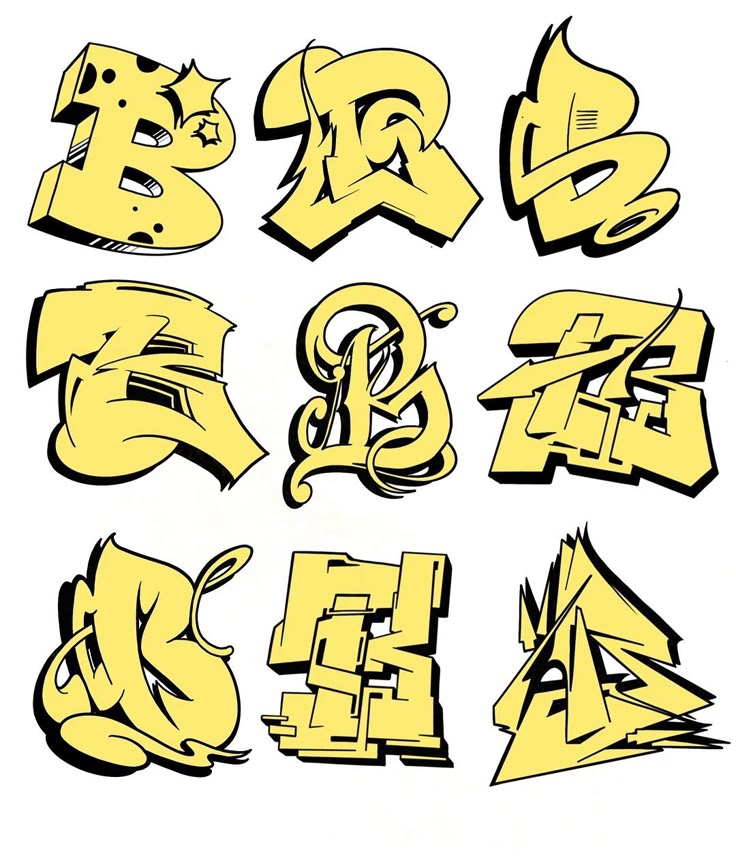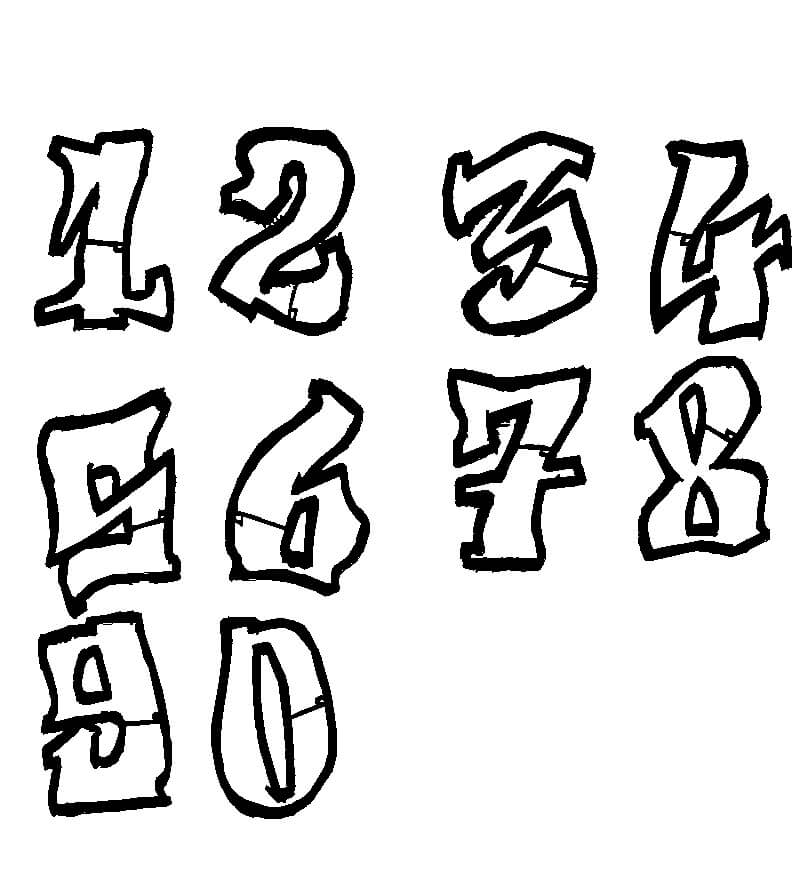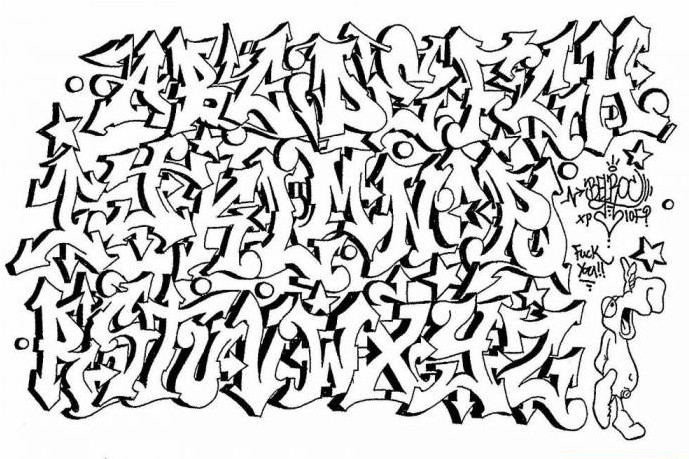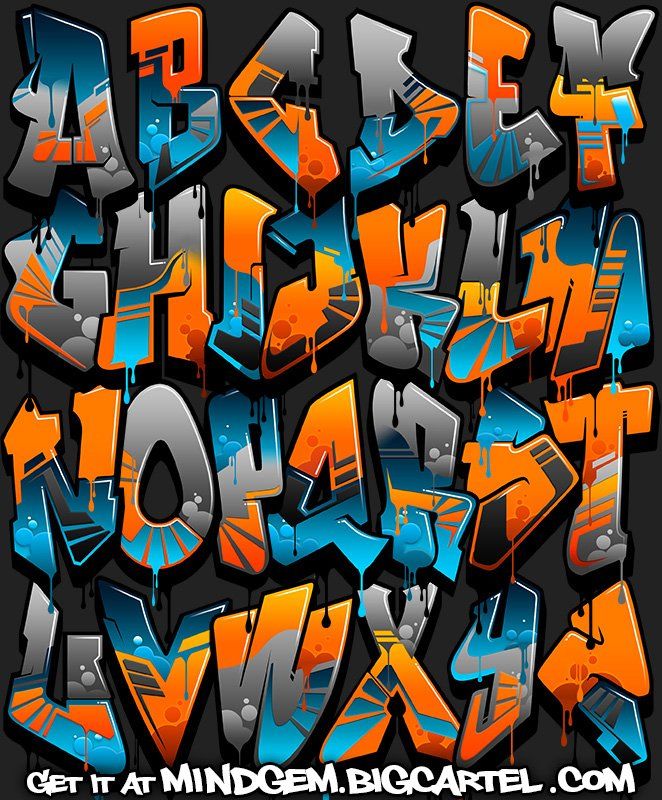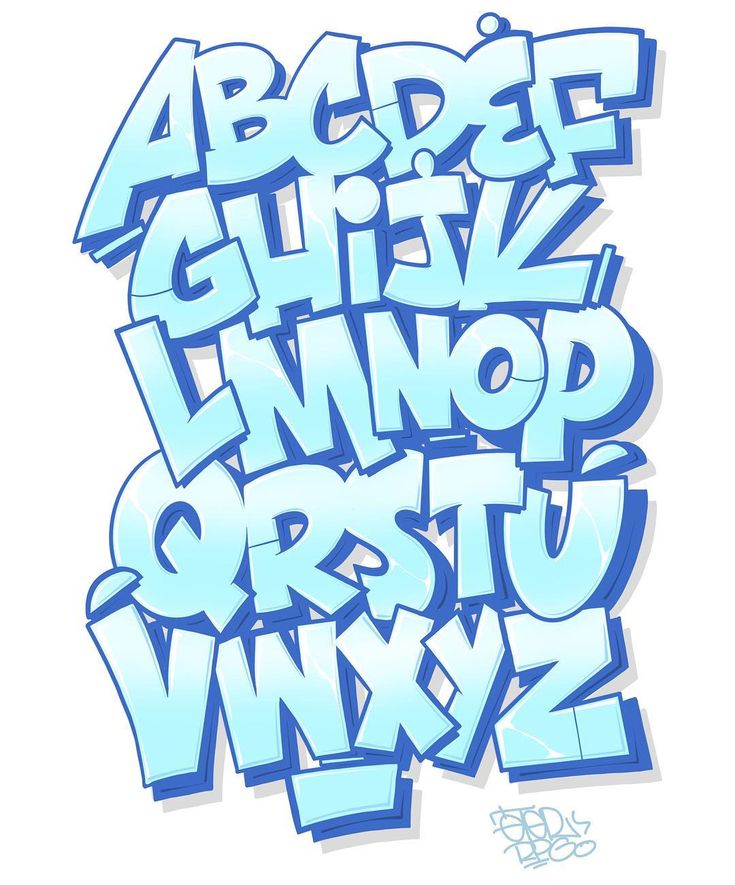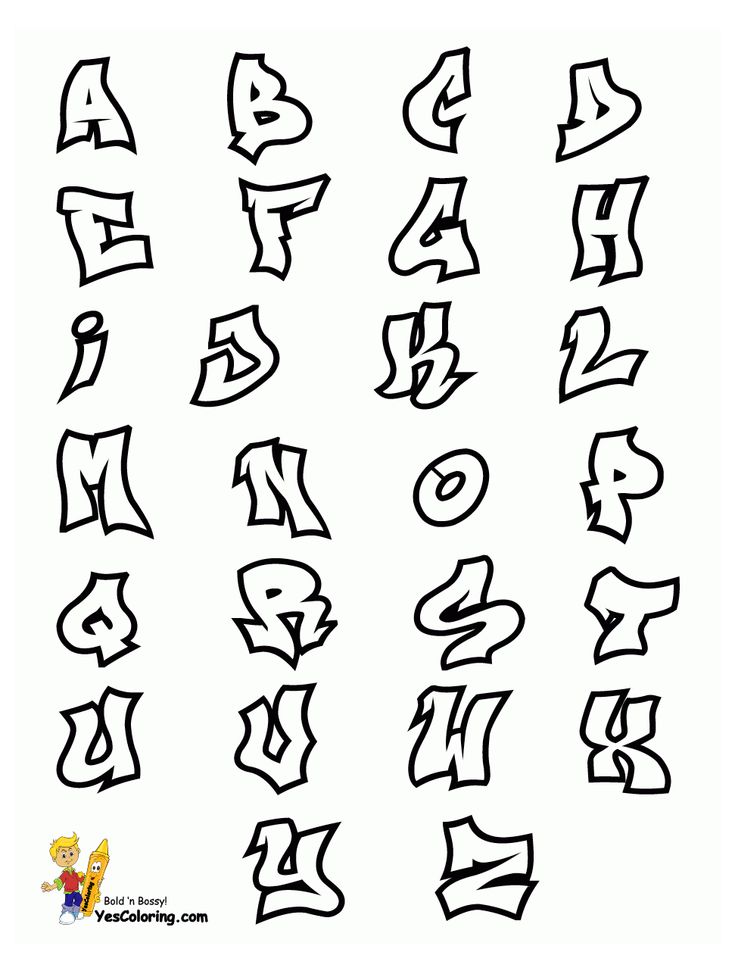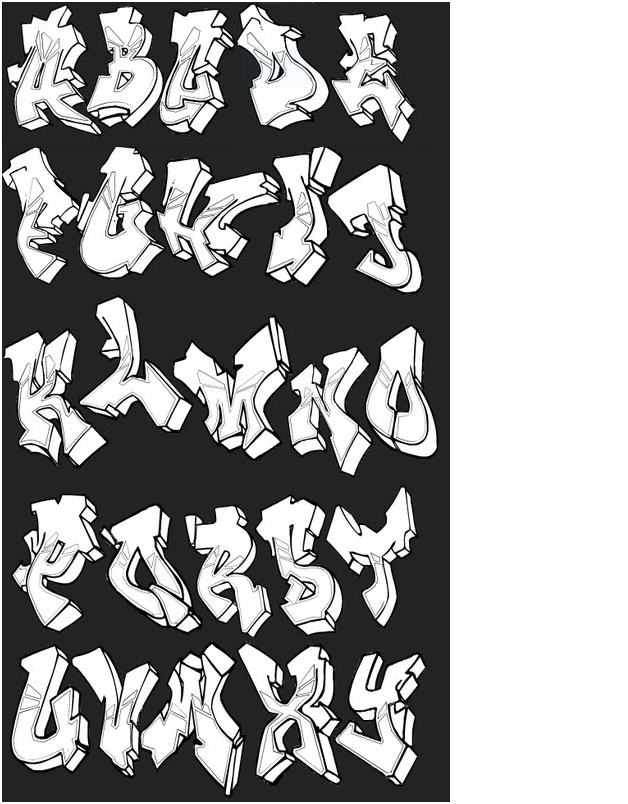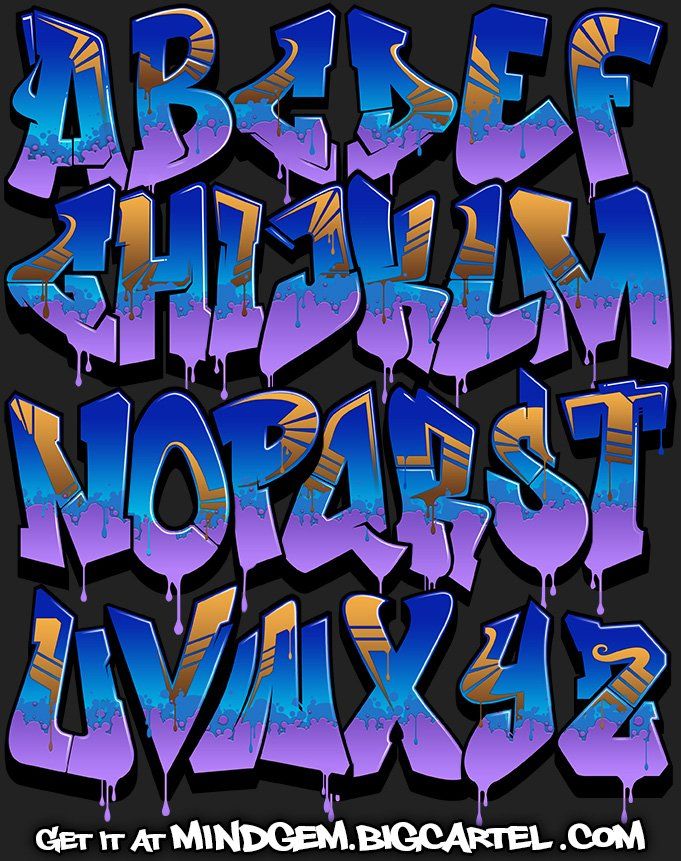
Вы ищете уникальный шрифт для дизайна вашего постера фильма или обложки журнала? Затем рассмотрите граффити-шрифт. Эти шрифты часто имеют уникальный дизайн и смелый вид, который привлекает внимание.
В этом посте мы собрали лучшие бесплатные шрифты граффити со всего Интернета. Большинство из них могут быть использованы бесплатно в личных проектах, но некоторые могут также использоваться в коммерческих проектах.
Hosp Graffiti
Шрифт Hosp был разработан для артистов. Это отличный выбор для любого современного проекта, который требует смелого внешнего вида. Шрифт включает заглавные буквы, цифры и знаки пунктуации. Это бесплатно для личного использования.
Sprite Graffiti
Шрифт Sprite поставляется в 3 различных стилях, и вы можете использовать его, когда вам нужен внешний вид граффити, но при этом вы хотите сохранить удобочитаемость. Шрифт является бесплатным для личного и коммерческого использования и поставляется с лицензиями на настольные и веб-шрифты.
MostWanted Graffiti
Шрифт MostWanted graffiti — это городской шрифт граффити с прописными и строчными буквами. Вы можете смешивать и сочетать их, чтобы создать уникальный дизайн. Шрифт включен в вашу подписку Envato Elements.
Tag Type Free
Шрифт Tag Type имеет прописные и строчные буквы, и вы можете скачать шрифт и использовать его в личных проектах бесплатно. Шрифт также содержит знаки препинания и кириллические символы.
Graffiti Front
Шрифт Graffiti — отличный способ украсить дизайн вашего постера фильма. Он имеет полный набор символов и может быть использован в личных и коммерческих проектах.
Sloppy Paint
Шрифт Sloppy Paint бесплатный для личного использования и включает в себя полный набор прописных букв, букв и знаков препинания.
The Graffiti
Этот шрифт Graffiti поставляется в черно-белой и цветной версии. Вы можете скачать его в формате PNG и использовать для личных и коммерческих проектов.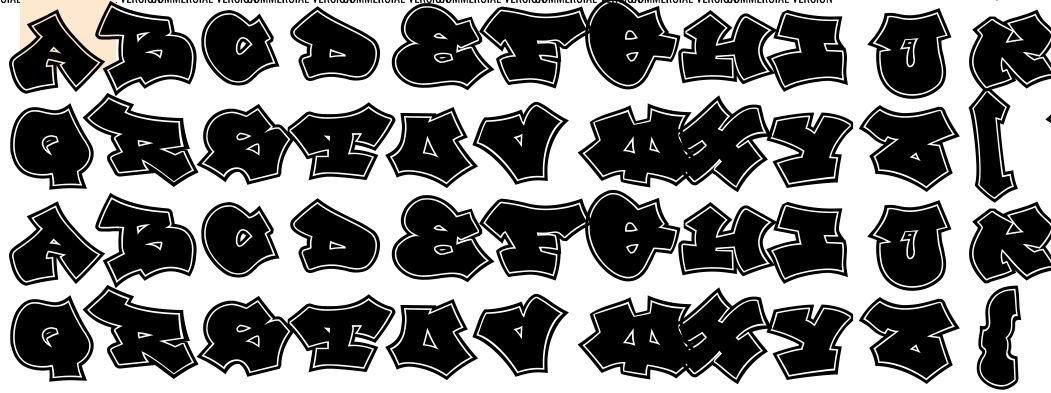
Don Graffiti
Шрифт Don Graffiti был вдохновлен старой школы граффити. Это бесплатно для личных и коммерческих проектов и является отличным выбором для постеров фильмов, демонстрации, обложек журналов и заголовков.
Baling Ink
Шрифт Baling Ink входит в вашу подписку Envato Elements. Это выразительный шрифт и отличный выбор для брендинга или дизайнерских проектов, которые хотят передать современный и городской стиль.
Brushed
Brushed Font бесплатен для личного использования. Он включает заглавные буквы, цифры и знаки пунктуации.
Marker No2Hun
Шрифт Marker No2Hun бесплатен для личного использования и включает в себя полный набор прописных и строчных букв, цифр и знаков препинания. Некоторые альтернативы также доступны.
Dexgraffiti
Dexgraffiti — это новый шрифт, который отлично подходит для современных городских проектов.
Он включает в себя полный набор прописных и строчных букв, а также цифры и знаки препинания.
Fusterd Brush
Шрифт Fusterd Brush Font имеет элегантный внешний вид. Вы можете использовать его для личных и коммерческих проектов. Шрифт поставляется с прописными и строчными буквами, цифрами и стилистическими чертами.
JuneBug
JuneBug — это игривый шрифт в стиле граффити, который идеально подходит для любого дизайнерского проекта, ориентированного на молодую аудиторию. Шрифт включает прописные и строчные буквы, цифры и знаки препинания. Это бесплатно для личного использования.
Fozzie Got A Posse
Этот шрифт включает в себя 3 различных стиля и полный набор прописных и строчных букв. Это также идет с цифрами и знаками препинания. Шрифт бесплатный для личного и коммерческого использования.
Serpong
Шрифт Serpong является прописным шрифтом, который включает сплошную и контурную версию.
Он является частью вашей подписки Envato Elements и поставляется с функциями OpenType.
Hoodson
Сценарий Hoodson — это смелый граффити-шрифт, который станет отличным выбором для постеров, заголовков или дизайна одежды. Это бесплатно для личного использования.
Rusto Fat Cap Brush
Rusto Fat Cap Brush — это персональный проект от дизайнеров Luis Di Lascio и Patri Pérez. Благодаря плавному стилю распылителя, он смелый и красочный.
Urban Decay
Urban decay — это художественный ручной шрифт, который создан Zofos для «празднования граффити, городских исследований, уличной каллиграфии и жизни в центре города». Этот шрифт — один из лучших шрифтов граффити, которые мы видели, с надежной аутентичностью, которая придаст городским ощущениям ваши проекты.
Philly
Philly Sans, разумеется, очень тяжелый, строчный шрифт с граффити, но при этом он чётко читается. Сделано Philatype, это отличный шрифт для отображения и абсолютно бесплатно для личного использования.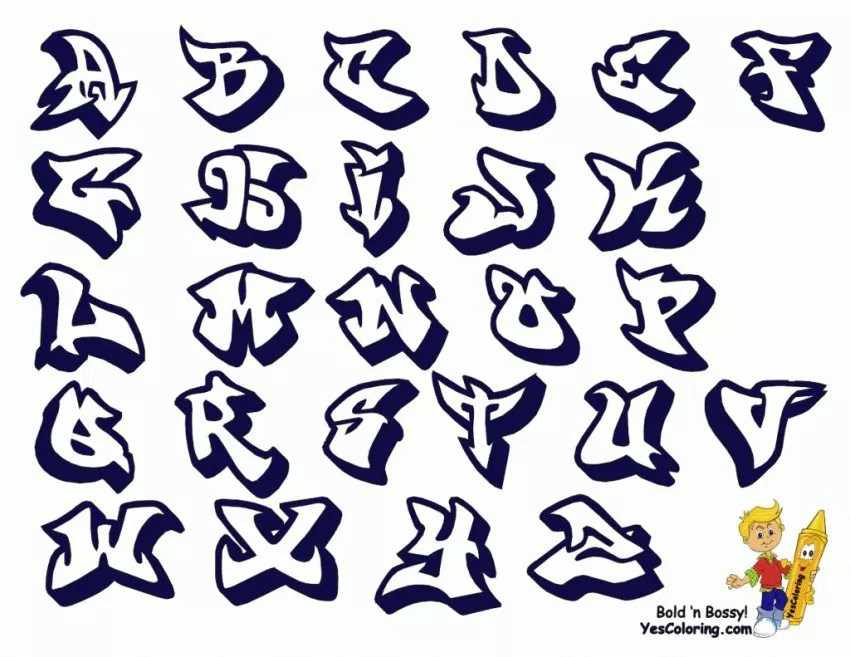
Knight Brush
Вдохновленный винтажной эпохой, Хендра Пратама создал этот шрифт с ручной росписью вывесок. Этот адаптируемый шрифт напоминает настоящие штрихи и является смелым выбором.